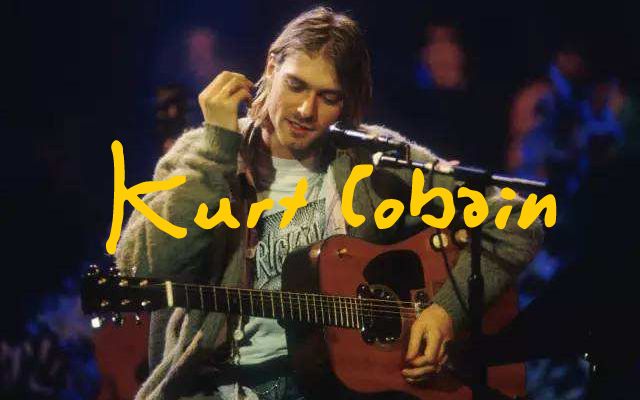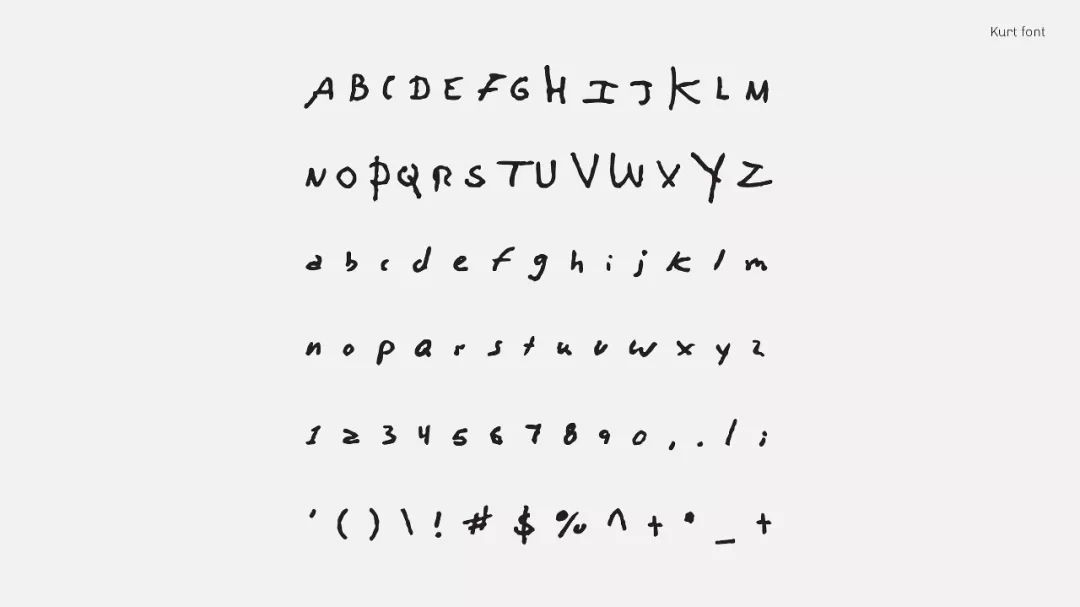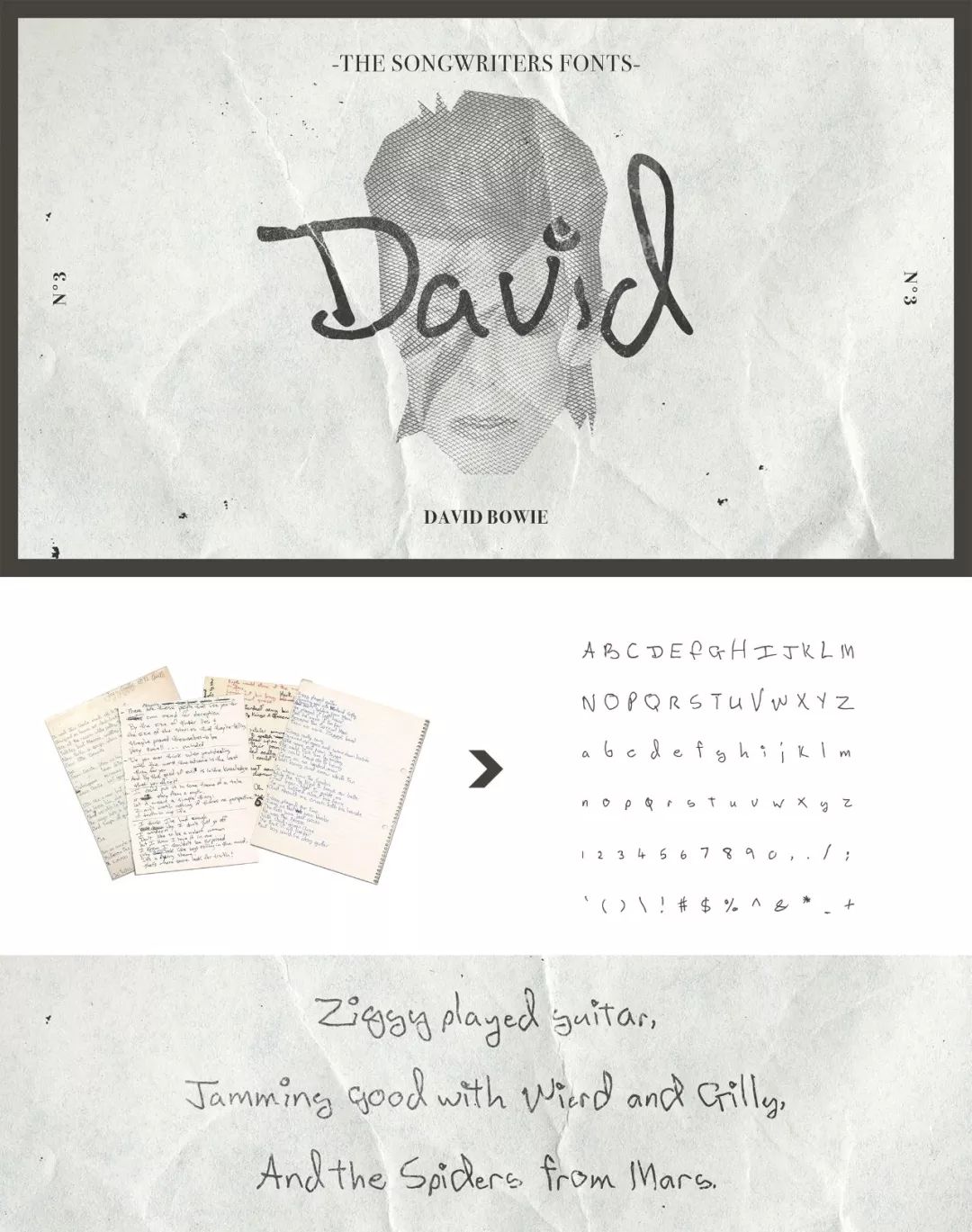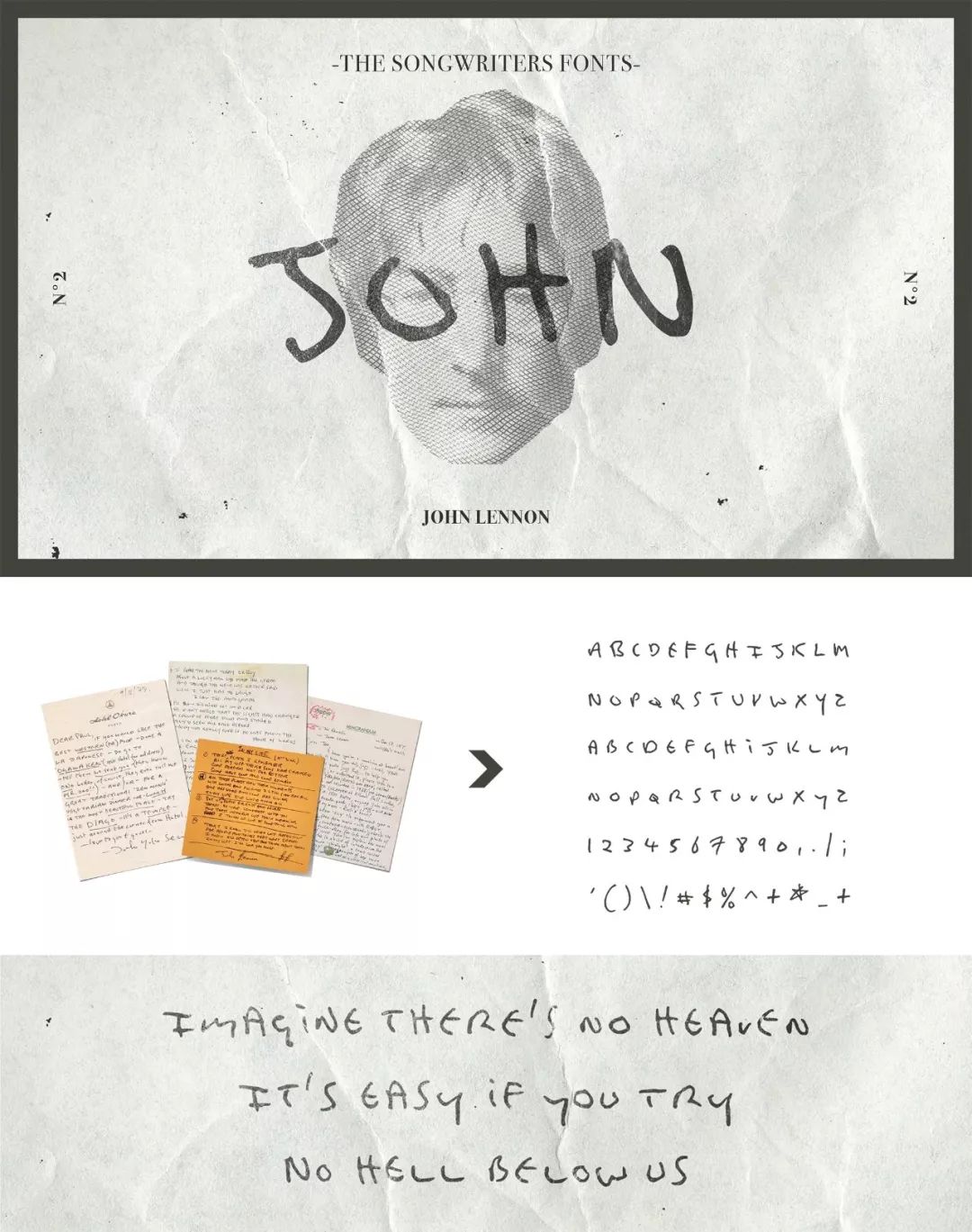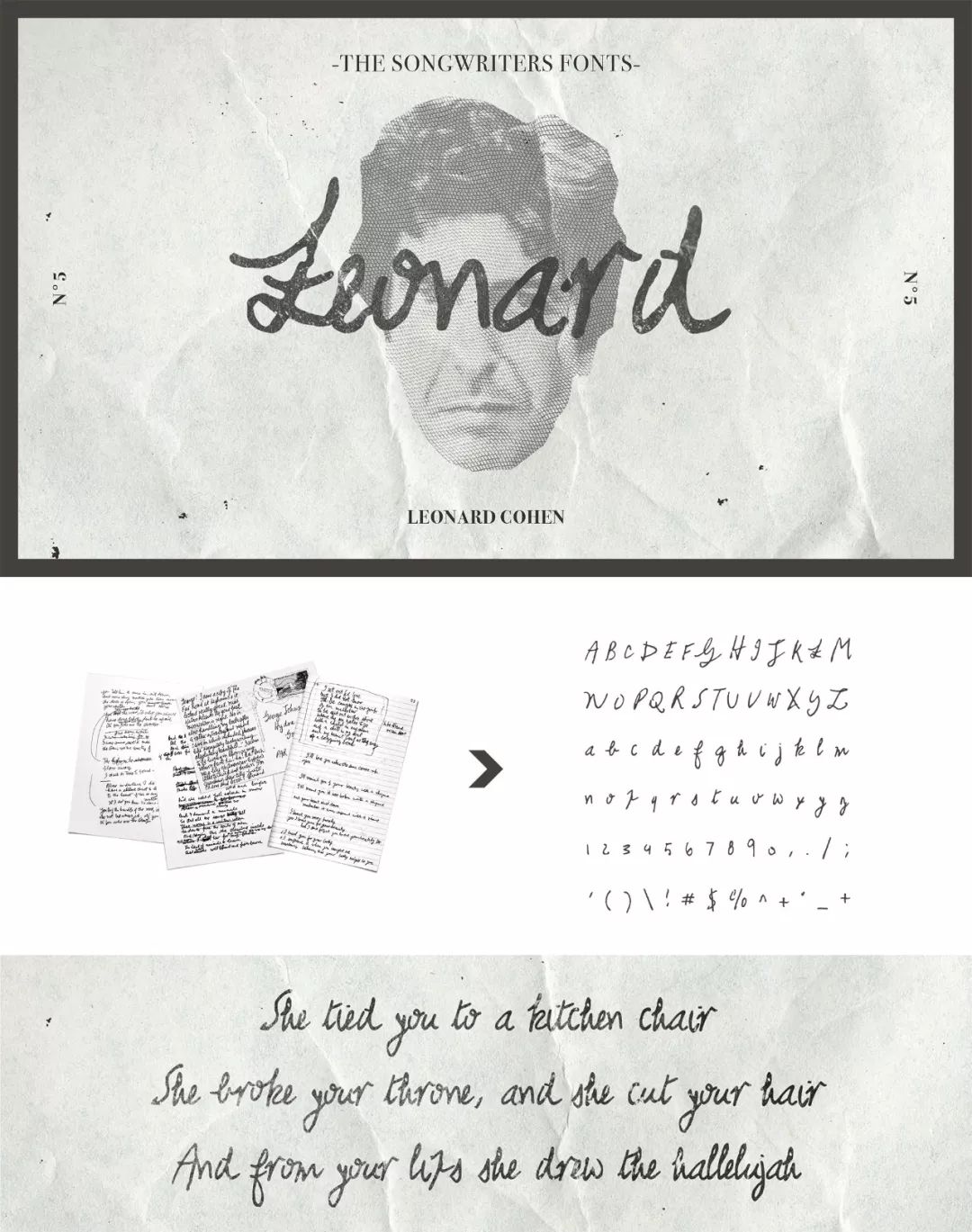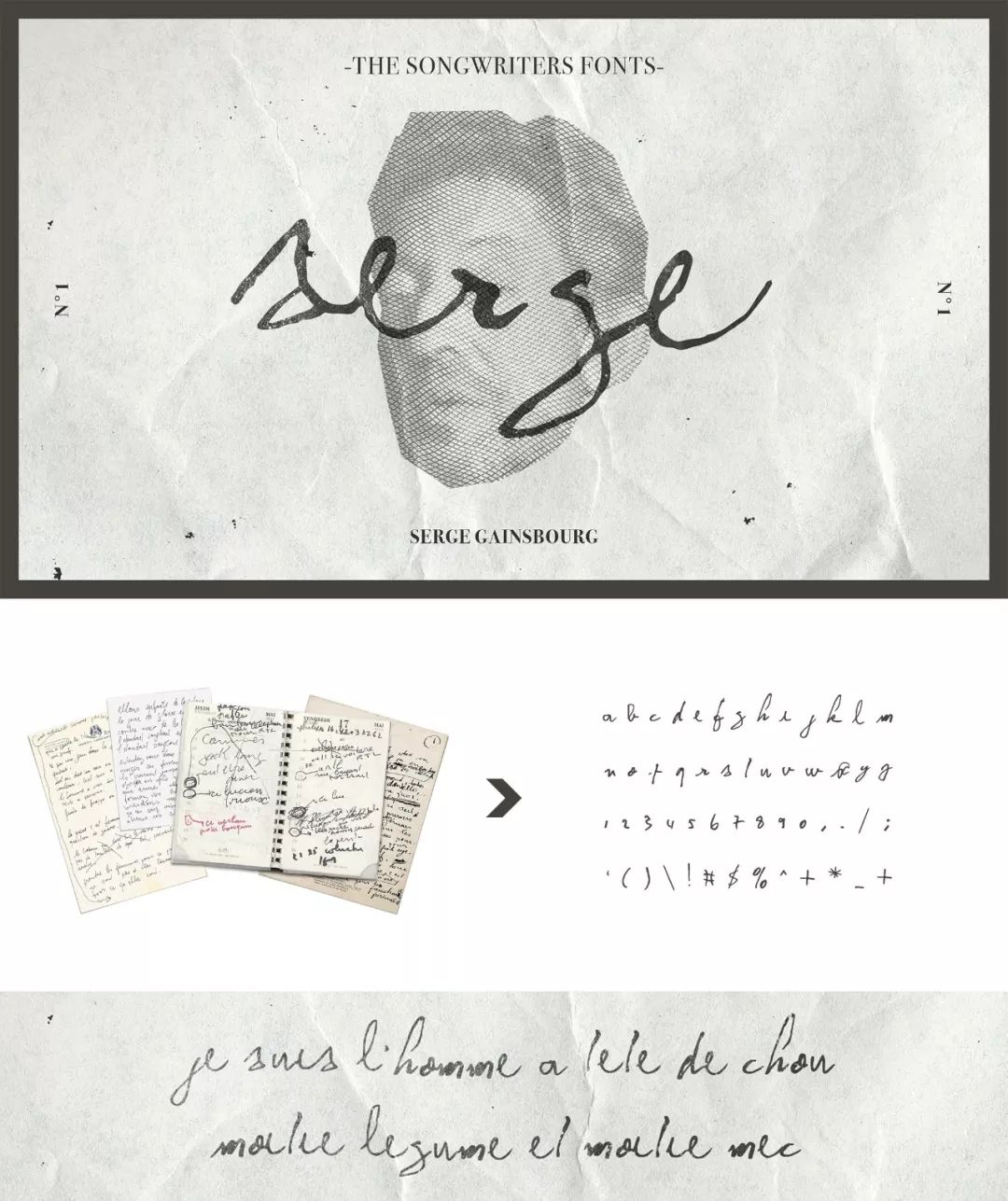
这5套传奇字体,居然都出自歌手的手稿
见字如面。一个人的字迹里承载了太多他们的经历和感情。去年台湾华康字体将 300 封手写情书制成数码字体。或许含有营销策略,但它对“我们如何证明存在”这个命题,给予了充满人情味的答复 -“因为文字,我们存在”。
当喜欢的歌手逝去,你会如何记住他们?通宵听他们的歌,看他们留下的影像文字,让他们活在我们的心里。但有人就偏偏想到了个使人会心一笑的方式 - 把歌手的笔迹做成数码字体。
△ 试用 David Bowie 字体打下的 “这里是麦芽”的英文
扫描、分析 5 位传奇音乐人的私人笔记和信件,甚至自杀留言,法国设计师 Nicolas damiens 和 Julien sens 制作了 5 套的字体。但“传奇传奇”了这么久,他们 5 位是何许人也?字是否如其人?(虽然上面不小心剧透了 David Bowie)
1. 矛盾孩子 Kurt Cobain (1992–1994)
如果 Kurt 知道自己所属的“涅槃乐队”入驻摇滚名人堂,他会气炸;如果他知道自己被评为“最伟大的词曲作者 100 名”之一,他会气死,虽然他早于 1994 年用 M-11 來福枪朝自己的头开了一枪。他将诚实感受写成歌曲,却眼睁睁看着它们变成大众商品。他矛盾他气自己,他最后的专辑里有首歌就叫《強暴我》。
△ 专辑《Nevermind》,下面将提到
这张击败 Michael Jackson 的专辑, 除了公开反对现代社会的物质主义,也在讽刺自己的乐团突然决定不做独立音乐。Kurt 最痛恨自己被媒体评论,所以我这里先打住。说字体。
△ 作为字体参考的 Kurt 的手稿
△ 完成后的字体,名为 Kurt-Regular
Kurt 的字迹潦草、不平。他偏爱粗体字,每一笔都仿佛篆刻,他甚至会用符号来替换形似的字母(比如 G)。就像他的词曲,关于诚实自我和伤痛,一颗 troubled soul。听着 Kurt 的歌,让我们了解另外 4 位音乐人。
2. 歌只是歌 John Lennon (1940-1980)
和 Kurt 一样,列侬在写歌时并没想代表什么,“我们只是在写歌罢了,歌词随着歌自然流露” 当然,他歌曲和个人活动依旧闪耀着人性。和“甲壳虫”团员 Paul McCartney 一同,他们创作的歌曲激励了数代的音乐人,Beatles 是种影响力。
△ 列侬的手写比 Kurt 的要“工整”稍许,没有那种“字母快要撞在一起的”感觉。
3. 黑星 David Bowie (1947–2016)
这人太逗了,我可以连续看他和乐队成员侃大山数小时不觉厌。1969 年的《Space Oddity》是他的第一首 hit song,而在 2013 年太空人 Chris Hadfield 真的在国际空间站录制了歌曲的翻唱 MV,一个圆满的轮回。因为是在外太空录制的,这首 MV 不受任何地球的版权法管制,还好 Mr Bowie 本人帮助解决了法律的纠纷。
△ Chris Hadfield 在外太空拍摄的《Space Oddity》
△ David-Regular 字体应用效果, 是 5 人中最生动的一款。
* 最麻烦的两款字体
“最费时的是收集手稿,之后会用字体软件数码化。比起这个,麻烦的还是制作 Leonard Cohen 和 Serge Gainsbourg 两人的字体。他们的手写体略带花笔 - 装饰性的曲线部分-我们要花时间塑造每个字母,以便让他们看起来是自然连着的。” 设计师苦笑着。
3. 香烟男人 Leonard Cohen (1934-2016)
“他将自己的天赋都献给了音乐事业。他是一个不懂得拒绝的铁血情人。Leonard 总是站在世界的巅峰。” Bob Dylan 评价 Leonard的影响力和冷静头脑
在他吟诵诗歌般的音乐里,你可能感到忧郁、也可以听出风趣、或者一丝丝性感,啊,还有禁欲。他是诗人,也是小说家。
2016 年歌手 Prince 去世那天,他引用旧曲《Who by Fire》的歌词表示自己也准备好了上路。他在最后专辑的《You Want It Darker》里唱道-I’m ready, my lord.
△ Leonard 的字里,有一位冷静的诗人
5. 全能野王子 Serge Gainsbourg (1928-1991 )
如果你喜欢法语的调调,又想尝试雷鬼乐,Serge 或许是你的茶杯。有着歌手、作曲家、音乐家、作家、演员、导演和画家各种名头,他唱过爵士、香颂、雷鬼、摇滚…无不信手拈来。
他因为把法国国歌改成雷鬼版遭到炸弹恐吓,在演唱会开场大唱《馬賽進行曲》,让那些右派退伍老兵不自觉起立跟唱。都暴露了,他们还怎么恐吓。
△ 同样带点花体,但 Serge 更放得开
后记
写到这里,犹如经历了 5 人份的人生。以字体为入口,我们听了 5 位音乐人的作品和故事。
不知你们觉得如何,反正我是想在睡前再多听听 Leonard Cohen 的歌,早晨起来公放 Serge Gainsbourg 的雷鬼,午后来一段 Kurt Cobain 的摇滚,下班前用耳机偷偷听 David Bowie。好像漏了什么,Hey Jude 我不听 Beatles 的。